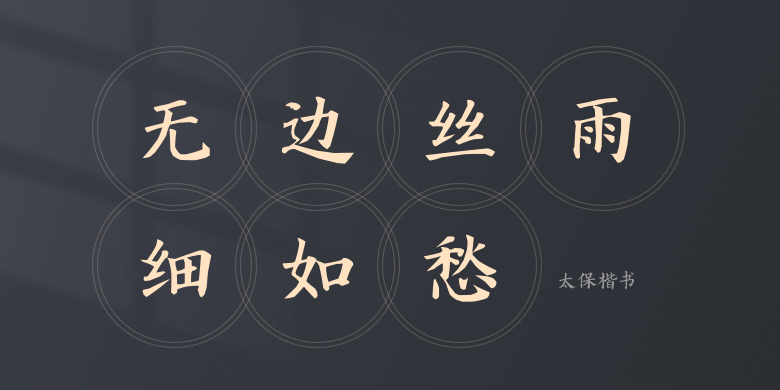
太保楷书
太保楷书,这款字体结构工整、笔画清晰,兼顾美观与易读性,适用于标题、正文、海报、包装、LOGO 等多种场景。字形优雅稳定,风格百搭耐看,适配日常排版与创意设计,让文字呈现更舒适、更具质感。太保楷书一笔一画,皆是细节,以均衡的比例、流畅的线条打造舒适视觉体验,字形端正大气,风格简约现代。无论是商业设计、品牌宣传还是日常排版,都能轻松驾驭,让文字更有格调与力量。太保楷书字体下载。